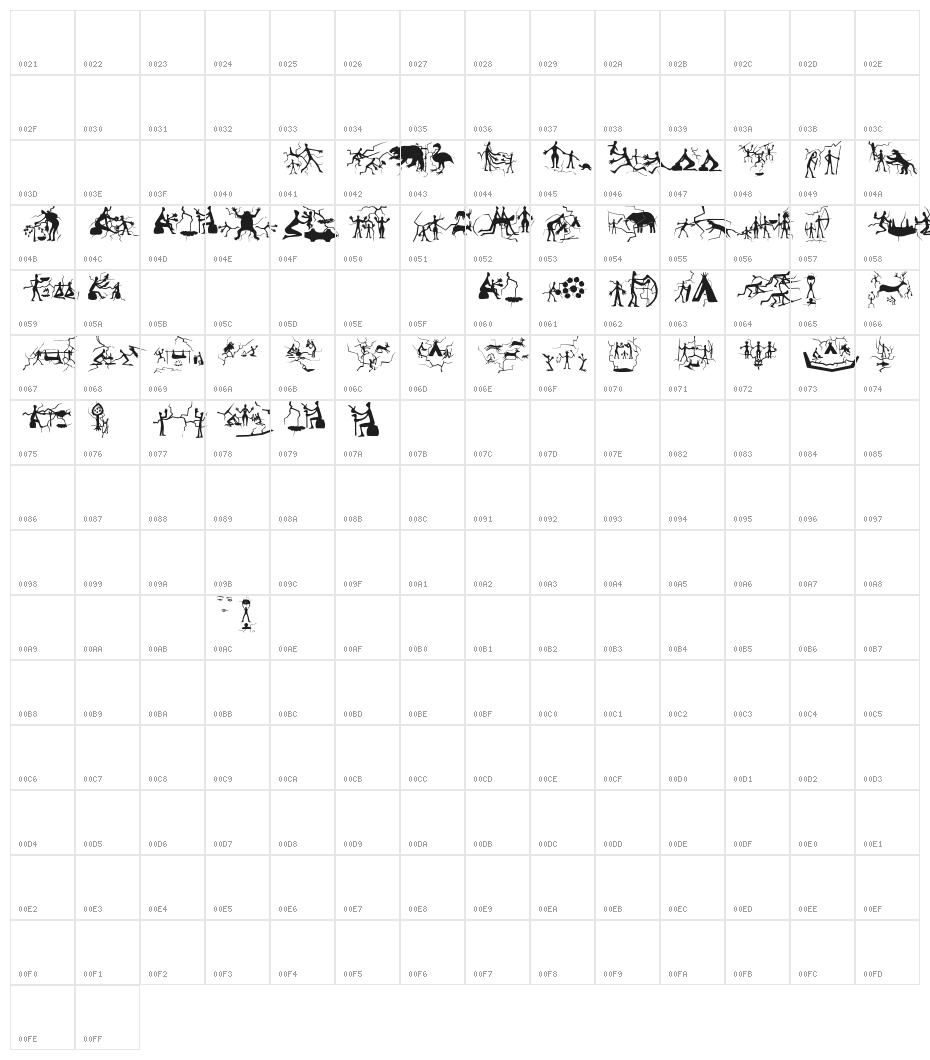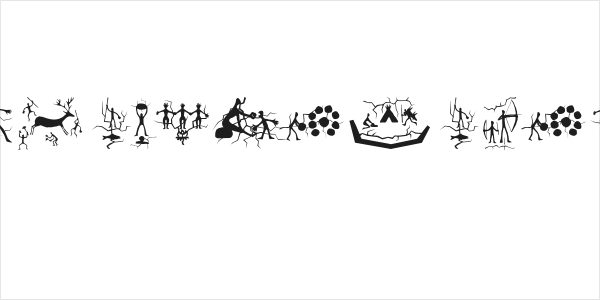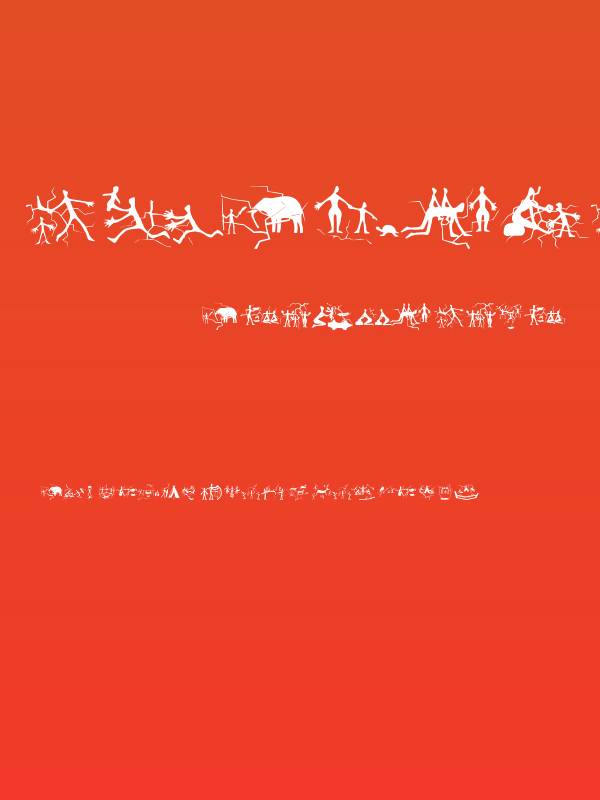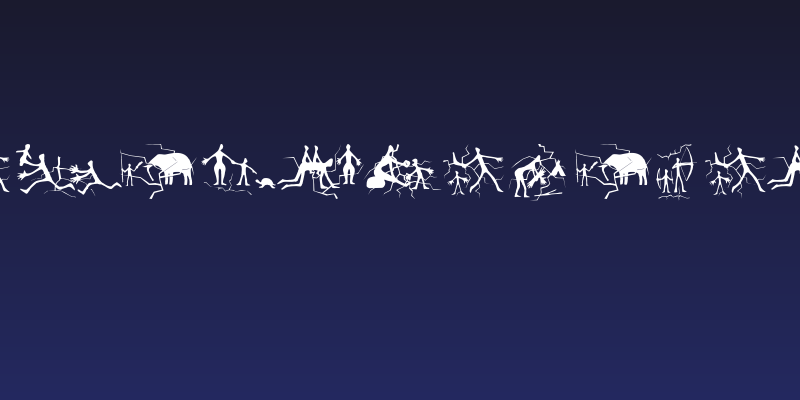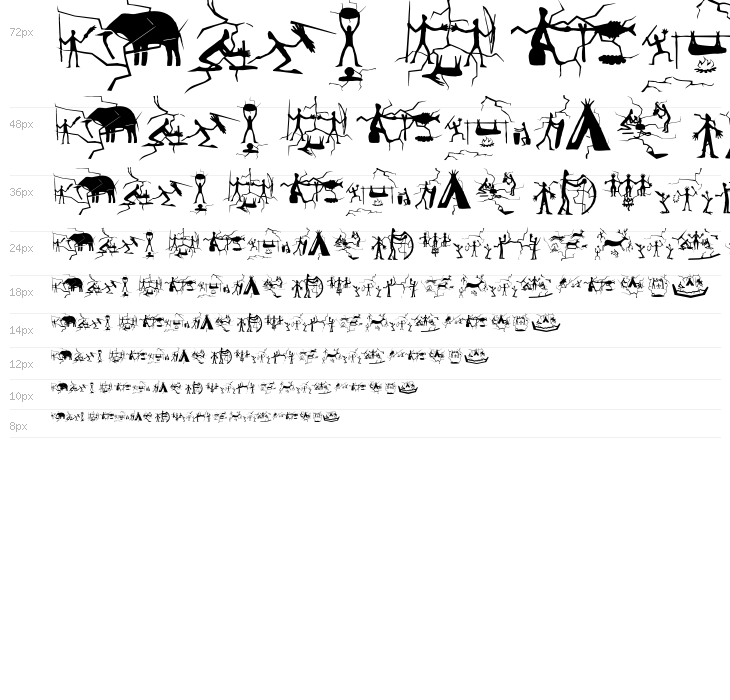
AfterLastWar Font
| Caso d'uso | Logos, Posters, Educational Materials |
| Progetti proposti | Ideal for historical documentaries, museum exhibits, educational materials, or any project that seeks to evoke a sense of ancient history and storytelling. |